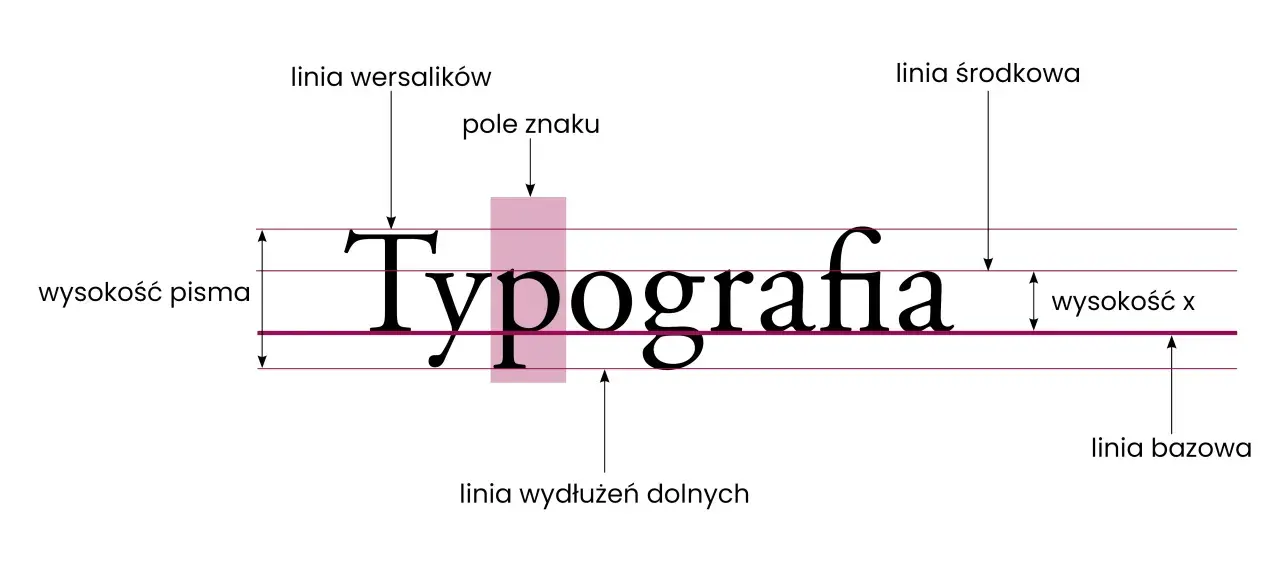
Typografia a kaligrafia - Przykłady, które zmieniają projekt
Typografia przykłady: linia bazowa, wysokość pisma, linia wersalików i śródkowa.
Typografia nie jest tylko wyborem ładnego kroju. To sposób, w jaki tekst prowadzi wzrok, buduje hierarchię i ustawia ton całego projektu. Poniżej pokazuję praktyczne przykłady z plakatów, książek, opakowań, materiałów biurowych i interfejsów, a przy okazji wyjaśniam, kiedy lepiej sięgnąć po typografię, a kiedy po kaligrafię. Dzięki temu łatwiej odróżnić efekt dekoracyjny od rozwiązania, które naprawdę działa w komunikacji.
Najlepsze przykłady pokazują, że czytelność, rytm i charakter muszą iść razem
• Typografia porządkuje treść, a kaligrafia dodaje gest i emocję.
• Najmocniej widać to w plakatach, książkach, opakowaniach, materiałach biurowych i UI.
• W tekście użytkowym zwykle wystarczą 1-2 kroje, poprawne odstępy i wyraźna hierarchia.
• Kaligrafia sprawdza się najlepiej jako akcent, nie jako długi blok treści.
• W drukowanych materiałach biurowych pierwszeństwo ma czytelność, spójność i oszczędność formy.
Czym różni się typografia od kaligrafii i dlaczego to zmienia projekt
Najprościej ujmując, typografia organizuje tekst, a kaligrafia nadaje mu ślad ludzkiej ręki. W praktyce oznacza to zupełnie inne cele, inne narzędzia i inne granice użycia. Ja patrzę na to tak: typografia ma przede wszystkim działać, a kaligrafia ma budować nastrój albo wyróżnić wybrany fragment.
Cecha Typografia Kaligrafia
Główny cel Czytelność, hierarchia i porządek informacji Ekspresja, charakter i wrażenie ręcznego zapisu
Narzędzia Kroje pisma, siatka, odstępy, interlinia, kontrast Pióro, stalówka, brush pen, brush lettering, pędzel
Najlepsze zastosowanie Plakaty, książki, raporty, strony WWW, instrukcje Zaproszenia, podpisy, cytaty, ozdobne nagłówki, logotypy
Ryzyko Sztywność albo chaos, jeśli hierarchia jest źle ustawiona Spadek czytelności, gdy styl dominuje nad treścią
To rozróżnienie ma znaczenie, bo zły wybór od razu zmienia odbiór projektu. Tekst, który ma informować, nie powinien zachowywać się jak dekoracja. Z kolei projekt, który ma budować emocję, nie może wyglądać jak zwykła notatka. To właśnie ten podział najczęściej decyduje, czy projekt czyta się płynnie, czy tylko wygląda efektownie.
Przykłady typografii w materiałach drukowanych
Najczytelniej typografia działa tam, gdzie tekst ma konkretną funkcję. W druku od razu widać, czy krój pomaga prowadzić wzrok, czy tylko zajmuje miejsce. W praktyce najczęściej analizuję trzy sytuacje: plakat, publikację i opakowanie.
Plakat i ulotka
Na plakacie typografia musi przyciągnąć uwagę z dystansu. Dlatego zwykle wygrywa mocny kontrast wielkości, krój o wyraźnym rysunku i ograniczona liczba słów. Dobry plakat często opiera się na 2-3 poziomach informacji: tytule, dacie lub haśle i krótkim doprecyzowaniu.
• Hasło główne powinno być krótkie, najlepiej 2-6 słów.
• Tekst pomocniczy musi być mniejszy, ale nadal czytelny w jednym spojrzeniu.
• Jeśli używasz kroju dekoracyjnego, zostaw mu rolę akcentu, a nie całego komunikatu.
W ulotce sytuacja jest odwrotna: czytelnik ma więcej czasu, ale też więcej treści do ogarnięcia. Tu dobrze działa prosty układ, wyraźne śródtytuły i spokojniejszy krój bez nadmiaru ozdobników. Jeśli projekt ma wyglądać profesjonalnie, to właśnie spójność siatki i odstępów robi większą różnicę niż „modny font”.
Książka i katalog
W publikacjach drukowanych typografia pracuje najciężej, bo tekst jest długi i czytany w skupieniu. Dlatego liczą się rzeczy pozornie mało efektowne: długość wiersza, interlinia, kontrast między nagłówkiem a tekstem podstawowym oraz dobór kroju do tempa czytania.
W praktyce dobrze sprawdzają się takie parametry: 45-75 znaków w wierszu, interlinia około 120-145% wielkości pisma i maksymalnie 1-2 rodziny krojów w całej publikacji. Dla tekstów użytkowych w druku często używa się też rozmiaru 10-12 pt, ale ostateczny wynik zależy od papieru, światła, grubości kroju i jakości druku.
Katalog produktowy powinien być bardziej uporządkowany niż efektowny. Jeśli produkt ma być oceniany przez pryzmat danych, specyfikacji i porównań, typografia ma pomóc w skanowaniu treści, a nie konkurować z fotografią. To dobry przykład, że czasem najlepszy projekt jest po prostu tym, którego nie trzeba poprawiać po pierwszym czytaniu.
Opakowanie i etykieta
Na opakowaniu typografia pracuje na bardzo małej powierzchni, więc każdy detal ma znaczenie. Najpierw trzeba odpowiedzieć sobie na pytanie, co klient ma odczytać w 3 sekundy: nazwę produktu, wariant, pojemność czy może obietnicę marki. Dopiero potem dobiera się styl.
Na małych etykietach ozdobny krój szybko staje się problemem, bo traci czytelność po zmniejszeniu. Z kolei zbyt neutralna typografia może nie wyróżnić produktu na półce. Dlatego w opakowaniach często działa układ mieszany: prosty, mocny krój dla nazwy oraz subtelny akcent, czasem właśnie kaligraficzny, dla wybranego słowa lub wersji premium.
W tym obszarze dobrze widać kompromis między estetyką a funkcją. Projekt ma wyglądać atrakcyjnie z bliska i z dystansu, a to wymaga większej dyscypliny niż w mediach społecznościowych. Właśnie dlatego opakowania są świetnym polem do nauki typografii w praktyce. W materiałach biurowych zasada jest podobna, tylko stawka jest jeszcze bardziej użytkowa.
Typografia w identyfikacji marki i materiałach biurowych
W dokumentach firmowych, prezentacjach, papierze firmowym czy notesach typografia nie może być przypadkowa. Tutaj projekt ma działać codziennie, a nie tylko robić pierwsze wrażenie. W firmie najbardziej cenie system, który da się powtarzać bez ciągłego zastanawiania się nad każdym slajdem czy nagłówkiem.
Jeśli mam wskazać praktyczny zestaw, to wygląda on zwykle tak:
• jeden krój podstawowy do treści i opisów,
• jeden krój albo jedna odmiana do nagłówków,
• stałe odstępy między nagłówkami, akapitami i listami,
• czytelny papier i kontrast, jeśli materiał ma być drukowany,
• ograniczona liczba wyróżnień, żeby dokument nie zaczął wyglądać chaotycznie.
W raportach i ofertach sprawdza się rozmiar tekstu 10-12 pt, a w prezentacjach warto pilnować, by nagłówki były wyraźnie większe od treści i nie ginęły na ekranie. Dobrą praktyką jest też zostawienie zapasu światła wokół bloków tekstu, bo dokument firmowy wygląda wtedy spokojniej i łatwiej się go skanuje wzrokiem. Dla materiałów biurowych to często ważniejsze niż sam wybór krójów.
W identyfikacji marki typografia pełni jeszcze inną funkcję: buduje rozpoznawalność. Ten sam zestaw liter na wizytówce, stopce maila, prezentacji i tabliczce przy recepcji tworzy wrażenie porządku. Jeśli każdy materiał wygląda inaczej, marka traci stabilność, nawet gdy pojedynczo wszystkie elementy są „ładne”. W praktyce właśnie spójność robi największą robotę.
Gdzie kaligrafia dodaje charakter, a gdzie przeszkadza
Kaligrafia jest świetna tam, gdzie projekt potrzebuje osobistego tonu. Najczęściej działa w zaproszeniach, nagłówkach wydarzeń, podpisach, cytatach, etykietach rzemieślniczych i wybranych elementach opakowań premium. Daje wrażenie ręczności, intymności i większej troski o detal.
Najlepiej traktować ją jak przyprawę, nie jak podstawę całego dania. Jeden dobrze użyty akcent kaligraficzny potrafi podnieść wartość wizualną projektu, ale ten sam styl w długim tekście szybko zaczyna męczyć. Im bardziej informacyjny materiał, tym ostrożniej trzeba z nim postępować.
• W zaproszeniach kaligrafia podnosi rangę komunikatu i sugeruje uroczysty charakter.
• W logotypach może nadać marce bardziej osobisty, rzemieślniczy ton.
• W cytatach i hasłach działa jako mocny akcent emocjonalny.
• W instrukcjach, regulaminach i dokumentach technicznych zwykle przeszkadza, bo obniża tempo czytania.
Jeśli projekt ma być czytelny dla szerokiego grona odbiorców, lepiej nie budować całej kompozycji na piśmie odręcznym. Kaligrafia świetnie wygląda na próbce, ale ostateczny test przechodzi dopiero wtedy, gdy trzeba ją odczytać w realnym użyciu. To prowadzi wprost do najczęstszych błędów, które psują nawet dobrze zapowiadający się projekt.
Najczęstsze błędy, które psują nawet dobry projekt
Większość problemów typograficznych nie wynika z braku dobrego kroju, tylko z braku dyscypliny. Widziałem projekty, które miały świetne fonty, a mimo to wyglądały słabo, bo ktoś dodał za dużo efektów albo nie zadbał o podstawy.
• Za dużo krojów - gdy w jednym projekcie pojawia się 4-5 fontów, treść przestaje mieć wspólny rytm.
• Zbyt mały kontrast - jeśli nagłówek i tekst podstawowy są do siebie za podobne, hierarchia po prostu znika.
• Ozdobny krój w długim akapicie - wygląda atrakcyjnie przez chwilę, ale szybko męczy czytelnika.
• Niepoprawne odstępy - zbyt ciasna interlinia albo tracking potrafią zniszczyć nawet dobry layout.
• Brak testu na realnym nośniku - projekt świetnie wygląda na monitorze, a po wydruku traci ostrość lub balans.
• Przesadna dekoracyjność - jeśli każdy element chce być ozdobą, całość przestaje być komunikatem.
Najprostsza zasada brzmi: najpierw ustaw strukturę, potem ozdobniki. Jeśli od początku określisz, co ma być nagłówkiem, co treścią, a co akcentem, projekt dużo rzadziej się rozsypuje. To samo dotyczy materiałów biurowych, w których chaos widać szczególnie szybko, bo użytkownik wraca do nich codziennie.
Co z tych przykładów warto przenieść do własnych projektów
Jeśli miałbym sprowadzić cały temat do jednej praktycznej myśli, powiedziałbym tak: dobry projekt typograficzny zaczyna się od funkcji, a dopiero potem szuka stylu. W plakatach liczy się szybkie uderzenie, w książkach rytm czytania, w opakowaniach rozpoznawalność, a w dokumentach firmowych - porządek i wygoda użytkowania.
Najbezpieczniejszy zestaw startowy to zwykle jeden krój podstawowy, jeden krój akcentowy i konsekwentna hierarchia. Gdy chcesz dodać kaligrafię, zostaw ją dla momentu, w którym ma coś podkreślić, a nie zagłuszyć. Jeśli projekt ma służyć ludziom w codziennym użyciu, prostota prawie zawsze wygrywa z fajerwerkami.
W praktyce najlepiej działa krótki test: czy odbiorca rozumie treść po 3 sekundach, czy widzi, co jest najważniejsze, i czy projekt nadal wygląda dobrze po wydruku albo na małym ekranie. Jeśli odpowiedź na te trzy pytania brzmi „tak”, typografia robi swoją robotę. Jeśli nie, zwykle problem nie leży w samym kroju, tylko w sposobie, w jaki został użyty.
FAQ - Najczęstsze pytania
Typografia to organizowanie tekstu dla czytelności i hierarchii (np. w książkach, na stronach WWW). Kaligrafia to sztuka pięknego pisania ręcznego, nadająca tekstowi emocjonalny, osobisty charakter (np. w zaproszeniach, logotypach).
Typografia jest kluczowa tam, gdzie liczy się czytelność i efektywne przekazywanie informacji. Idealnie sprawdza się w plakatach, książkach, raportach, interfejsach użytkownika (UI) oraz materiałach biurowych, zapewniając porządek i spójność.
Kaligrafia dodaje projektom osobistego charakteru i elegancji. Jest idealna do zaproszeń, ozdobnych nagłówków, logotypów, cytatów czy etykiet produktów premium, gdzie ma podkreślić unikalność i nadać emocjonalny ton.
Do najczęstszych błędów należą: zbyt wiele krojów pisma, brak kontrastu, używanie ozdobnego kroju w długich akapitach, niepoprawne odstępy (interlinia, tracking) oraz brak testów na realnym nośniku. Psują one czytelność i estetykę.
Dobra typografia zaczyna się od funkcji. Stosuj jeden krój podstawowy i jeden akcentowy, dbaj o konsekwentną hierarchię treści i testuj projekt na różnych nośnikach. Prostota i czytelność zawsze wygrywają z nadmierną dekoracyjnością.